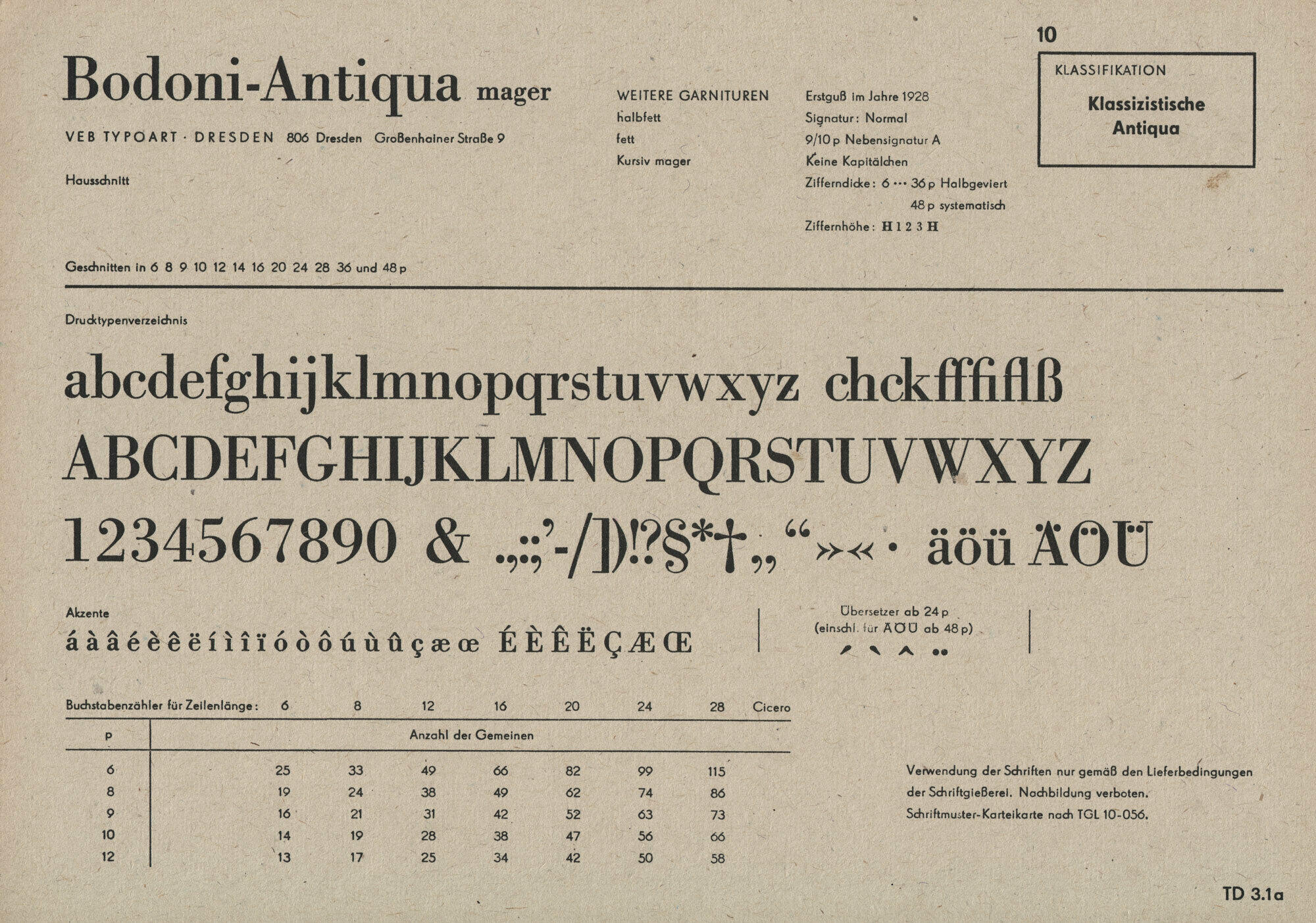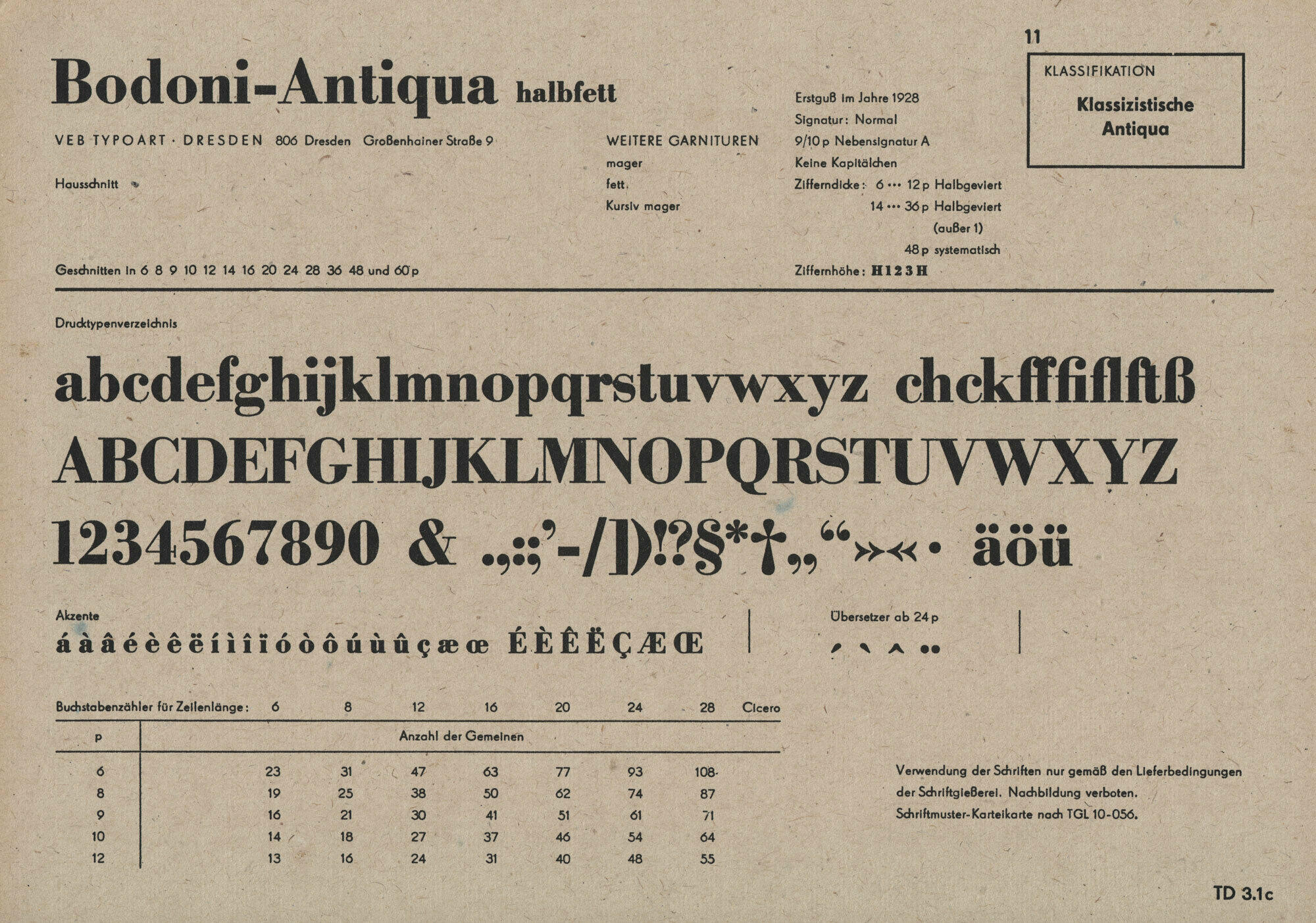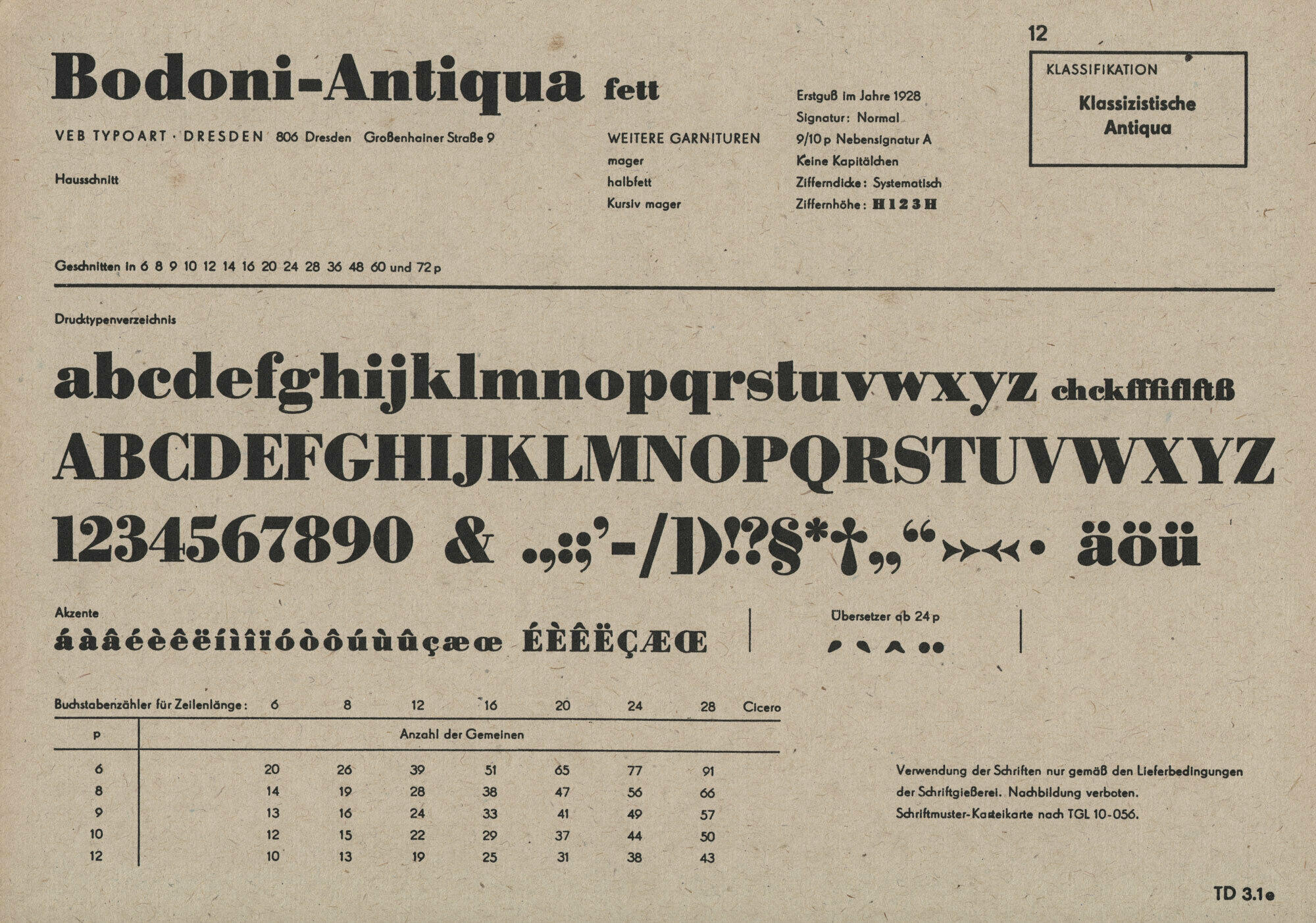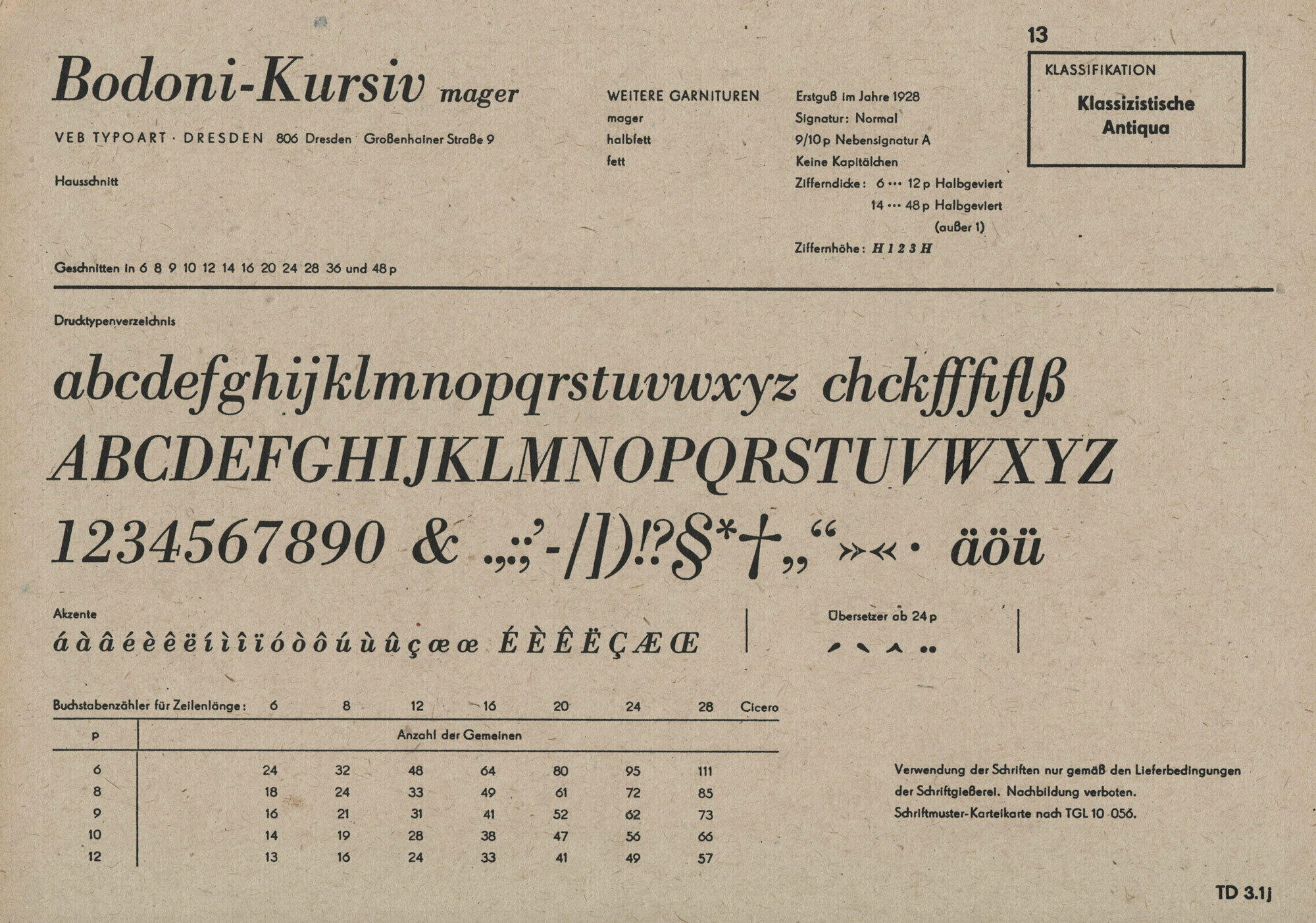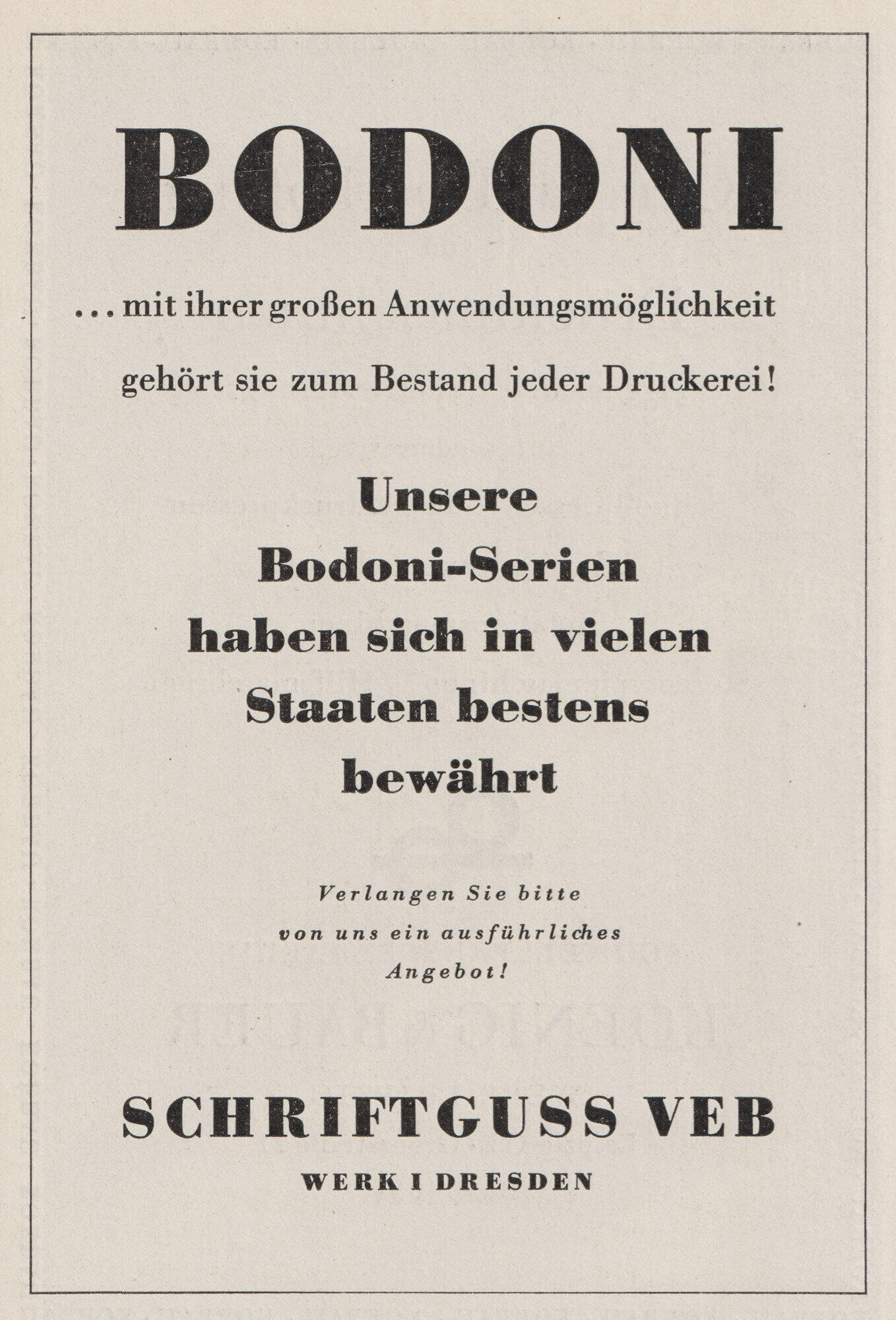
Font-Wiki: Bodoni (Schriftguss/Typoart)
Diese Bodoni-Version erschien in den 1920er-Jahren als Bleisatzschrift bei der Dresdner Schriftguss AG. Es gab vier Hausschnitte ohne Gestalterangaben: mager, kursiv, halbfett und fett. Nach dem 2. Weltkrieg wurde die Schriftfamilie über den VEB Schriftguss und schließlich den VEB Typoart weiterhin angeboten, wurde aber in den späteren Hauptproben nicht mehr gezeigt.